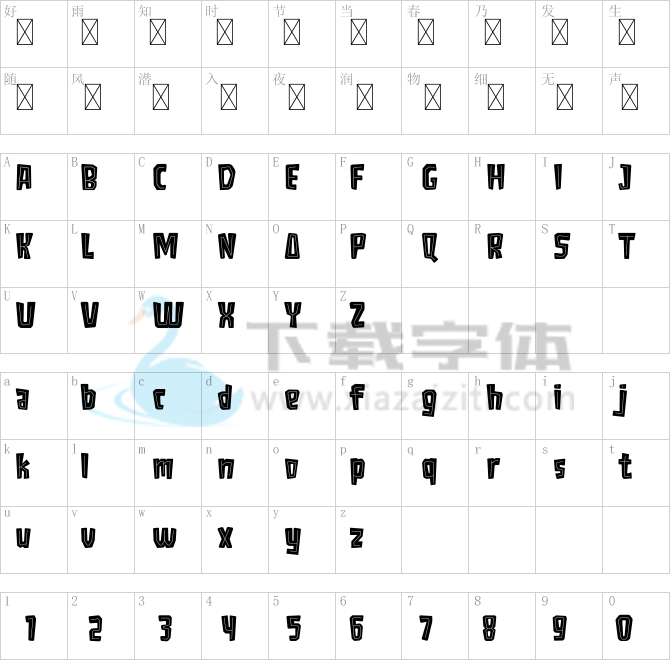
Alpaloza.otf字体下载,这款字体结构工整、笔画清晰,兼顾美观与易读性,适用于标题、正文、海报、包装、LOGO 等多种场景。字形优雅稳定,风格百搭耐看,适配日常排版与创意设计,让文字呈现更舒适、更具质感。Alpaloza.otf字体下载一笔一画,皆是细节,以均衡的比例、流畅的线条打造舒适视觉体验,字形端正大气,风格简约现代。无论是商业设计、品牌宣传还是日常排版,都能轻松驾驭,让文字更有格调与力量。Alpaloza.otf字体下载字体下载。